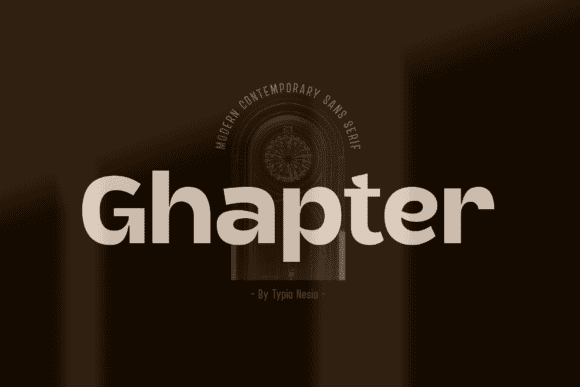
Название: Ghapter Font
Ghapter - смелый, но невероятно четкий шрифт без засечек.
Он имеет стильный, элегантный и современный вид, который может быть использован для логотипов, брендинга, приглашения, канцелярские принадлежности, свадебный дизайн, сообщения в социальных сетях, и многое другое!